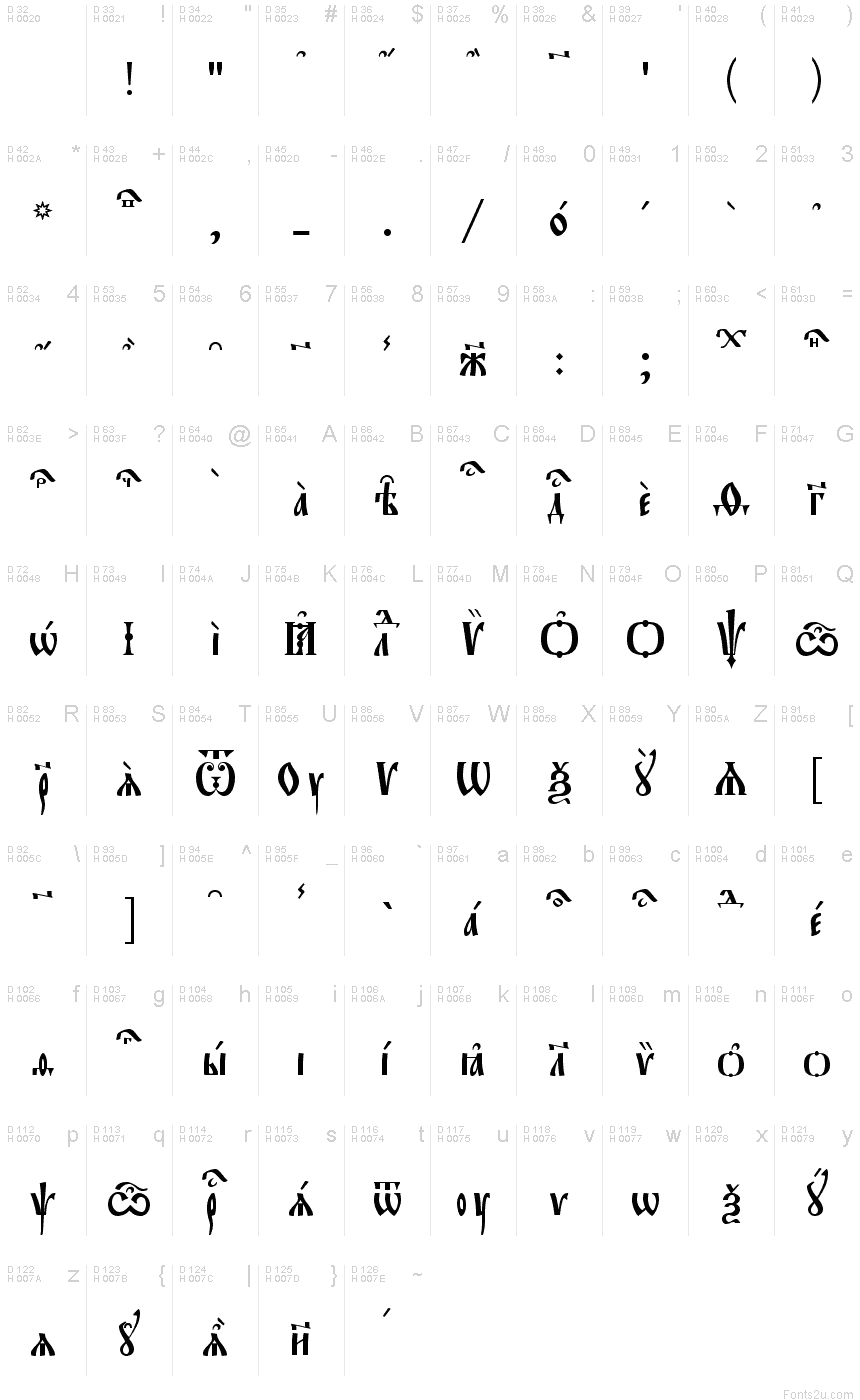
Orthodox TT UCS8 SpacedOut di SoftUnion Ltd e N. Andrushchenko è un font display gratuito che richiama l'atmosfera dei libri ecclesiastici e delle iscrizioni sulle icone. Le lettere uniscono un movimento calligrafico stretto a forme arrotondate solenni, mentre gli accenti a punto, i ganci e le piccole tacche affilate conferiscono al set un ritmo liturgico distinto.
È ideale per titoli di locandine di musica sacra, copertine di libri di storia slava, grafica per mostre, bollettini parrocchiali e packaging devozionale, dove il sapore del manoscritto antico deve essere percepito come una scelta culturale piuttosto che come un generico stile medievale. Essendo un font gratuito, funziona bene anche per monogrammi, carte di intestazione e iniziali, poiché questi segni insoliti e le forme cerimoniali distanziate infondono molta atmosfera anche in poche lettere.
Orthodox font is intended for publishing liturgical texts in Church Slavonic language. This font created on the basis of the font Evangelie by N. Andrushchenko